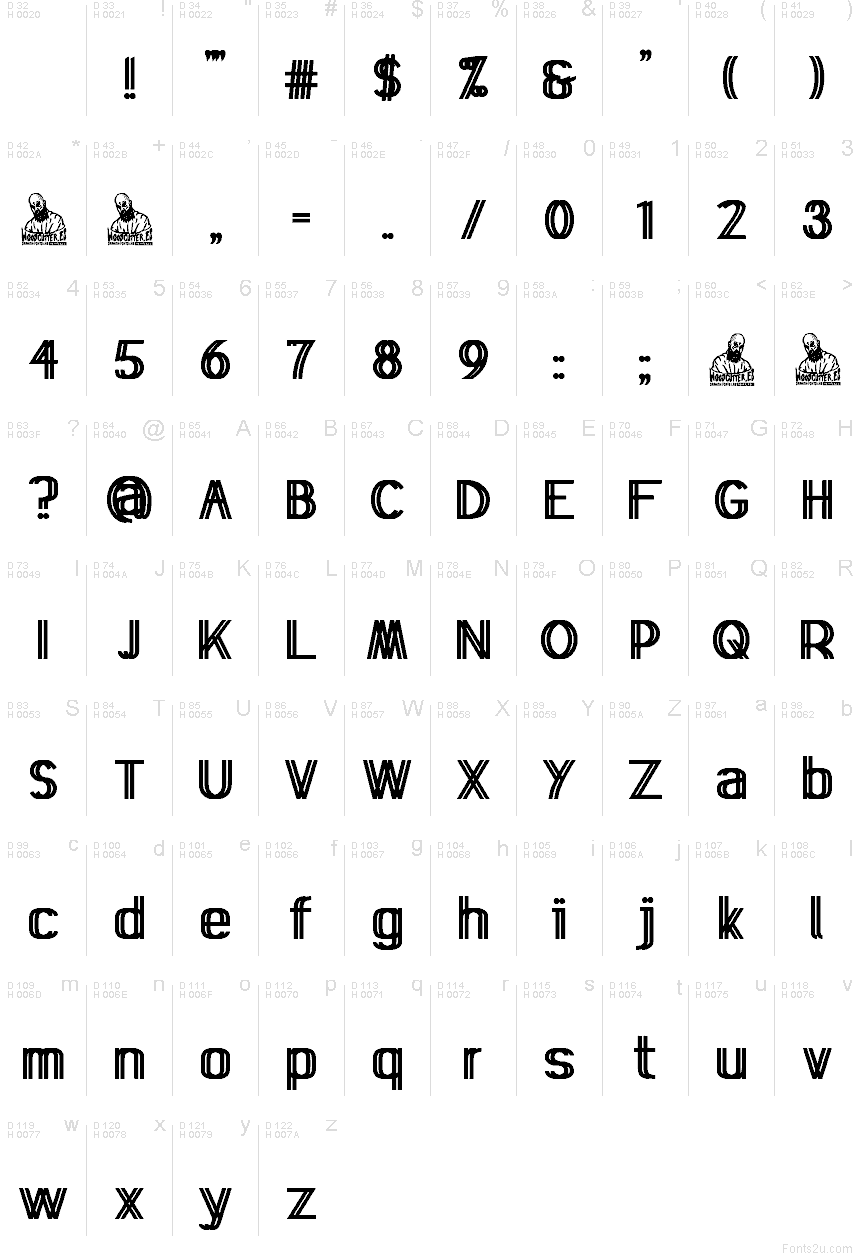
Podgląd czcionki The Secretary
The Secretary autorstwa Woodcutter Manero MMXXII to darmowy krój pisma typu display w stylu secesyjnym (Art Nouveau), wyróżniający się wysokimi, eleganckimi literami i klimatem starych plakatów. Wąskie pionowe linie, zaokrąglone łuki i prążkowane wykończenie nadają literom szlachetnego, niemal gabinetowego charakteru, balansując gdzieś pomiędzy dawnymi szyldami a ozdobnym liternictwem.
Doskonale pasuje do brandingu kawiarni, kart menu koktajli, okładek książek, opakowań typu boutique oraz nagłówków plakatów, gdzie pożądany jest dekoracyjny, historyczny rys bez popadania w pełen wiktoriański styl. Jako darmowy font, świetnie sprawdzi się również w tytułach, monogramach i krótkich tekstach redakcyjnych, ponieważ jego wydłużone proporcje i wewnętrzne prążki same w sobie budują cały styl.